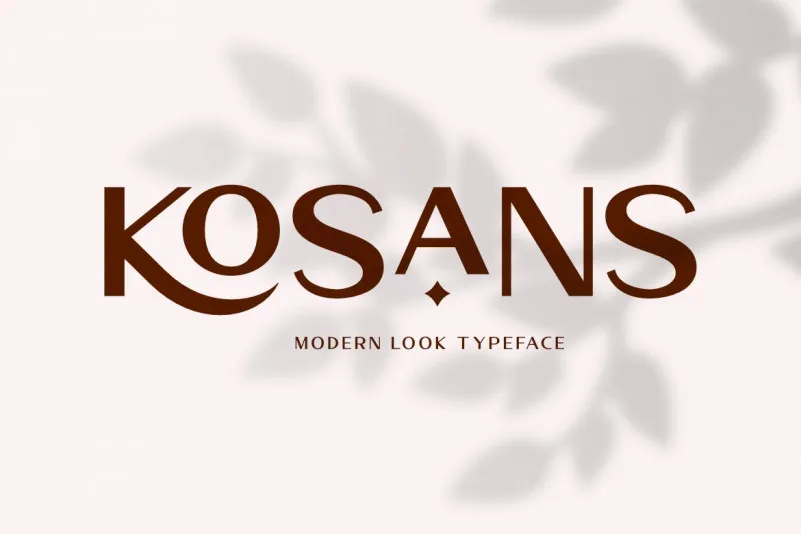
Kosans é uma fonte tipo sans serif que combina influências modernas com traços do passado, criando uma sensação de nostalgia e prazer em conhecer novidades. Esta elegante fonte é perfeitamente adaptável a diversos tipos de projetos gráficos: desde logotipos e cartões de visita até perfis nas redes sociais ou citações inspiradoras. É perfeita para qualquer designer que busque uma solução versátil, moderna e nostálgica para suas criações digitais. Com Kosans, você pode criar designs impactantes em um amplo espectro de aplicabilidades, garantindo a sua identidade visual se destacando na era digital.